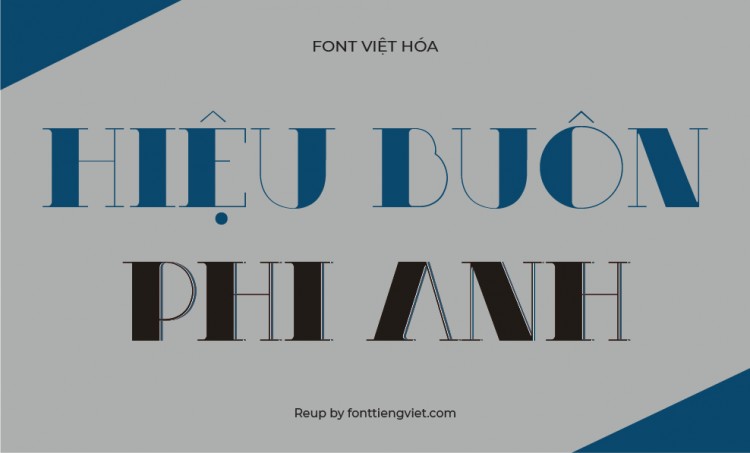
Font việt hóa FS Fabrizio
Giới thiệu về bộ Font việt hóa FS Fabrizio trong thiết kế
Trong thế giới đồ họa hiện đại, việc lựa chọn một bộ Font Miễn Phí chất lượng luôn là ưu tiên hàng đầu của các nhà thiết kế chuyên nghiệp lẫn các bạn học sinh sinh viên. Font việt hóa FS Fabrizio nổi lên như một giải pháp hoàn hảo nhờ sự kết hợp tinh tế giữa phong cách cổ điển và hơi thở đương đại. Đây là bộ phông chữ thuộc phong cách Serif (có chân) nhưng được tinh chỉnh với các đường nét thanh mảnh, tạo cảm giác thanh lịch và vô cùng sang trọng. Việc sở hữu Font việt hóa FS Fabrizio giúp các tác phẩm thiết kế tiếng Việt không còn bị lỗi dấu, mang lại sự chỉn chu và tính thẩm mỹ cao nhất cho mọi dự án từ in ấn đến hiển thị kỹ thuật số.
Đặc điểm nổi bật của FS Fabrizio việt hóa
Bộ Font việt hóa FS Fabrizio sở hữu những đường cong mềm mại phối hợp cùng các góc cạnh sắc nét, tạo nên một cấu trúc chữ vững chãi nhưng không kém phần uyển chuyển. Điểm mạnh của bộ font này chính là khả năng đọc tốt (readability) ngay cả ở kích thước nhỏ, giúp người xem dễ dàng tiếp nhận thông tin trên các tài liệu giáo dục hoặc slide thuyết trình. Đặc biệt, bộ Font việt hóa FS Fabrizio đã được xử lý dấu tiếng Việt cực kỳ mượt mà, đảm bảo sự đồng bộ giữa các ký tự nguyên âm và phụ âm, không gây hiện tượng nhảy dòng hay lệch dấu thường gặp ở các font nước ngoài chưa qua hiệu chỉnh.
Ứng dụng Font việt hóa FS Fabrizio vào thực tế giảng dạy và thiết kế
Với sự phát triển của công nghệ giáo dục, việc sử dụng các phông chữ đẹp như Font việt hóa FS Fabrizio trong soạn thảo bài giảng đang ngày càng phổ biến. Các thầy cô giáo có thể ứng dụng bộ chữ này để tạo ra các tiêu đề bắt mắt trên bảng tin lớp học hoặc các tài liệu hướng dẫn học tập sinh động. Trong thiết kế đồ họa chuyên nghiệp, Font việt hóa FS Fabrizio là lựa chọn lý tưởng cho các ấn phẩm tạp chí, bìa sách, nhận diện thương hiệu thời trang hoặc menu nhà hàng sang trọng. Sự thanh thoát của nó giúp tôn vinh giá trị nội dung và tạo dấu ấn riêng biệt cho người sử dụng.
Lý do nên ưu tiên Font việt hóa FS Fabrizio cho dự án
Một trong những lý do khiến Font việt hóa FS Fabrizio được yêu thích chính là sự linh hoạt và khả năng tương thích cao trên nhiều phần mềm thiết kế như Photoshop, AI hay các công cụ văn phòng Microsoft Office. Khi kết hợp bộ chữ này với các tông màu trung tính, bạn sẽ tạo ra một không gian thị giác chuyên nghiệp và đẳng cấp. Ngoài ra, việc sử dụng Font việt hóa FS Fabrizio giúp tiết kiệm thời gian chỉnh sửa lỗi font, cho phép người dùng tập trung hoàn toàn vào việc sáng tạo nội dung chất lượng cao cho cộng đồng người dùng Việt Nam.
Kết luận và trải nghiệm Font việt hóa FS Fabrizio ngay hôm nay